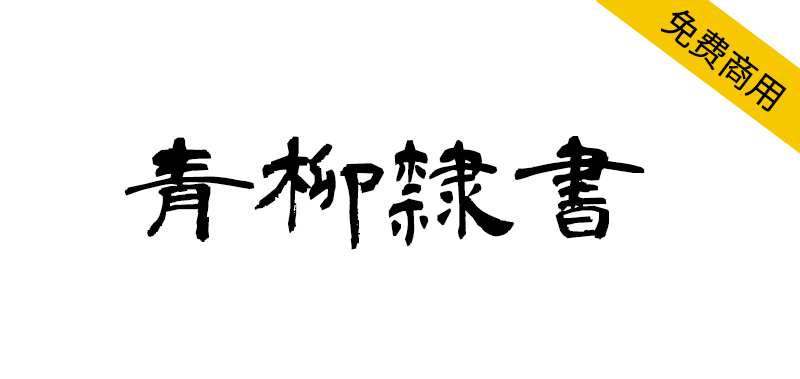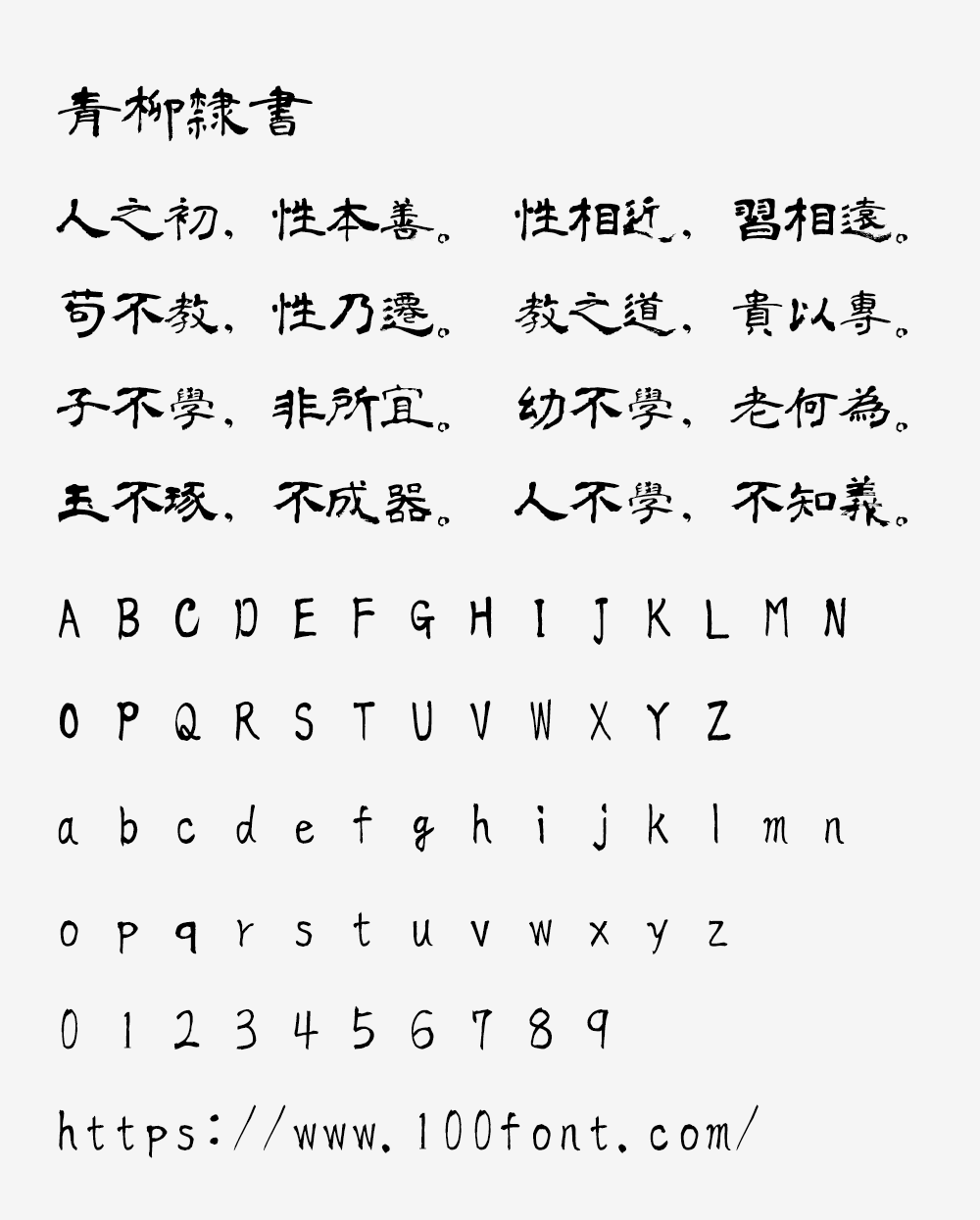
【青柳隶书】日本书法家青柳衡山老师隶书字体
青柳隶书(青柳隷書しも),由日本书法家青柳衡山老师题字,然后由SIMO先生制作成TrueType字体。这款字体包含JIS第1水准2965字,第2水准3390字。由于字体采用的日本的JIS标准,所以支持的简体字数不是很多,但是繁体却是比较齐全的。
書家の青柳衡山先生が揮毫されたものを、SIMO様が作成されたTrueTypeフォントです。無料でご利用できます。JIS第二水準までに収録されています。著作権はSIMO様がお持ちです。
【青柳隶书】日本书法家青柳衡山老师隶书字体